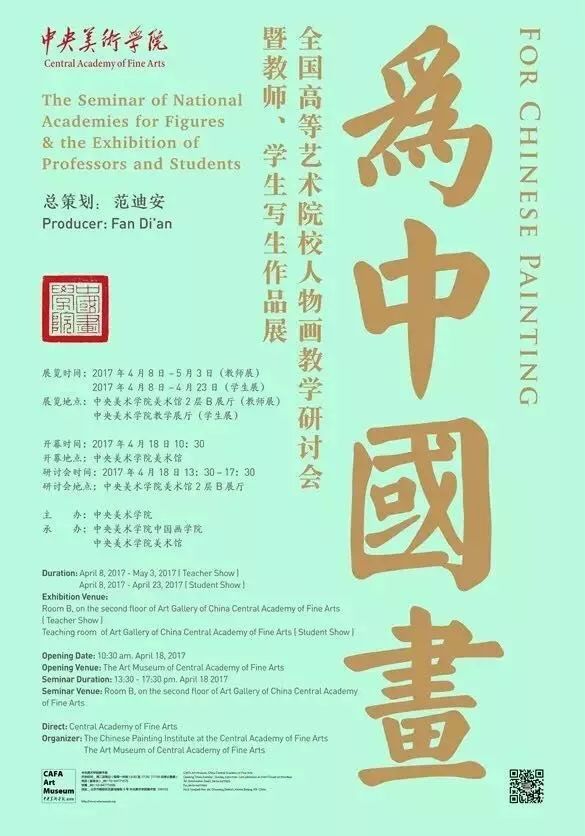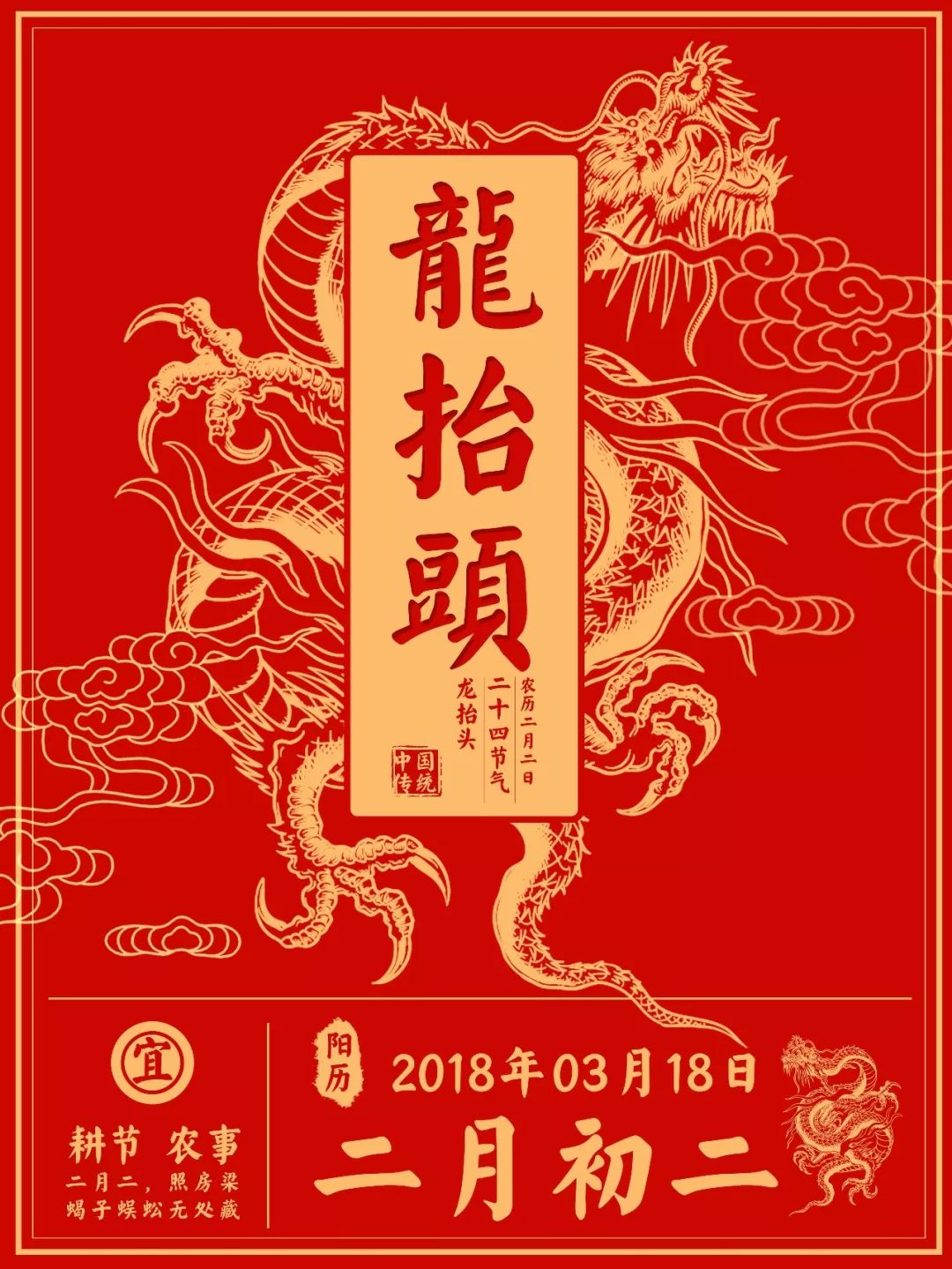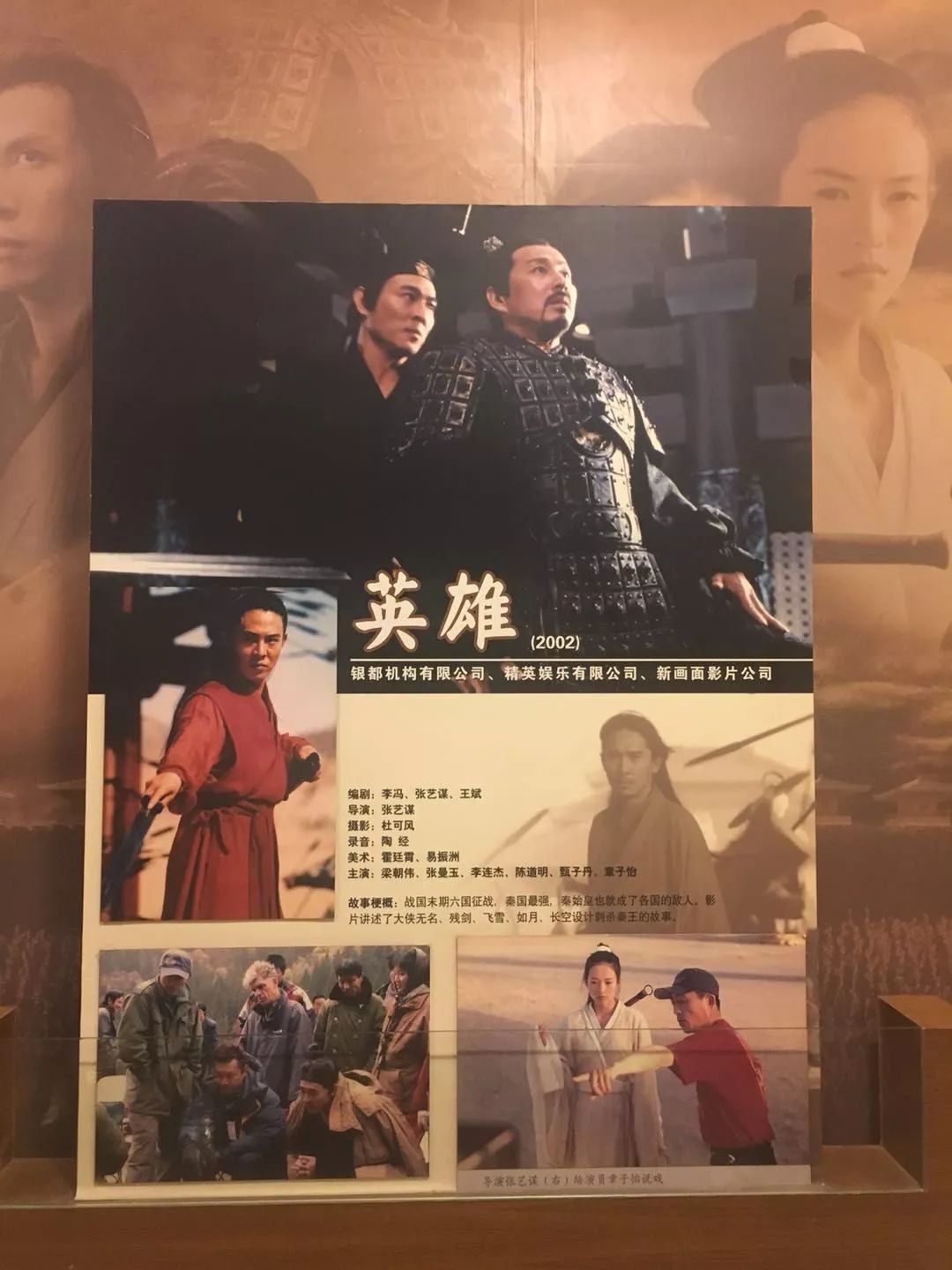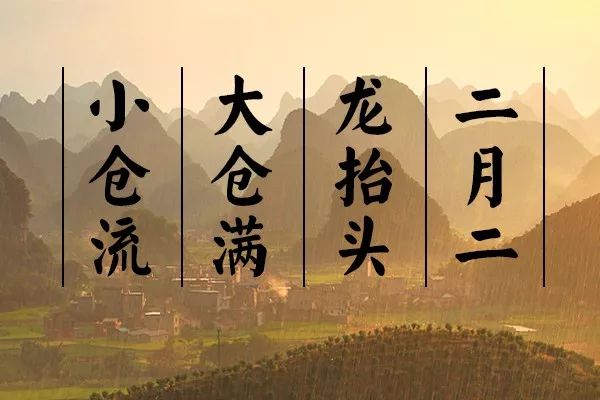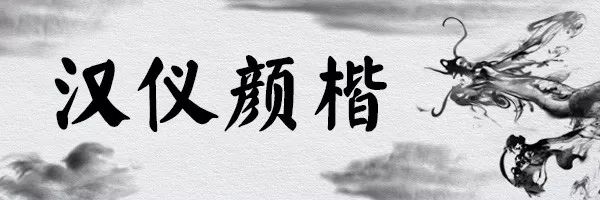
汉仪颜楷字体介绍, 汉仪颜楷使用案例分享
“二月二、龙抬头、剃毛头”
在民间,尤其是北方汉族地区,
二月二这天朋友联系不上别心急,
因为他们不在家,就在理发店,
不在理发店,就在去理发店的路上。
作为一个古老的习俗,
二月二“剃头”这件事,
已经深深烙印在大家的脑子里。
同时坊间也流传着,
“二月二剃龙头,一年都有精神头”等说法!
那为什么一定要在这天“剃头”呢?
农历二月初二,春回大地,
正是作物播种的时节,大地渴求雨水的滋润。
龙在中国文化里是主宰风雨的祥瑞之物,
俗语里有“龙不抬头天不雨”一说。
因此龙抬头是复苏和吉祥的象征,
人们选择在这一天剃头,
以期许鸿运当头的好彩头。
在人们心中,
“龙”寄托着生存和希望。
“龙”就是信仰,
它让我们始终相信,
无论贫穷还是富裕,无论艰辛还是顺遂,
对美好的渴求,
是对生活的永不失望。
因此,
在这个充满喜庆和祝愿的日子里,
一定要有一款可以满满的足够表达这一传统的字体,
那么,这里怎么能少的了“颜楷”的身影?!
其行笔浑厚有力,笔画内敛不外露
结构严整茂密,看似肥硕臃肿
但行笔间笔画张弛有度舒展流畅毫不呆板
从而形成了丰腴雄伟的书风
这不恰恰与中国“龙”的精神相当的吻合
如此有古风的字体
用在传统节庆之中便再合适不过了!
【鼎力推荐】
文化类场景